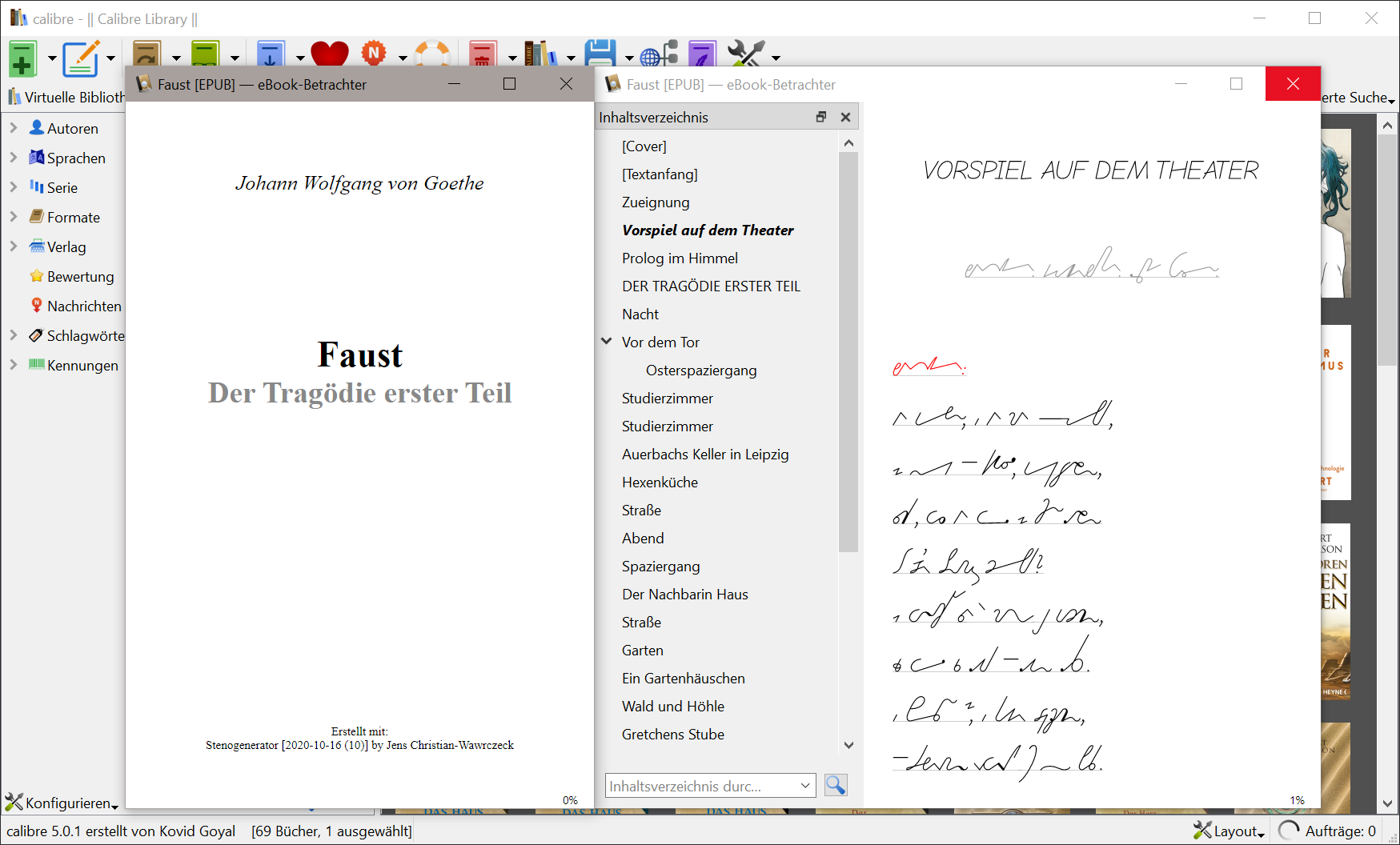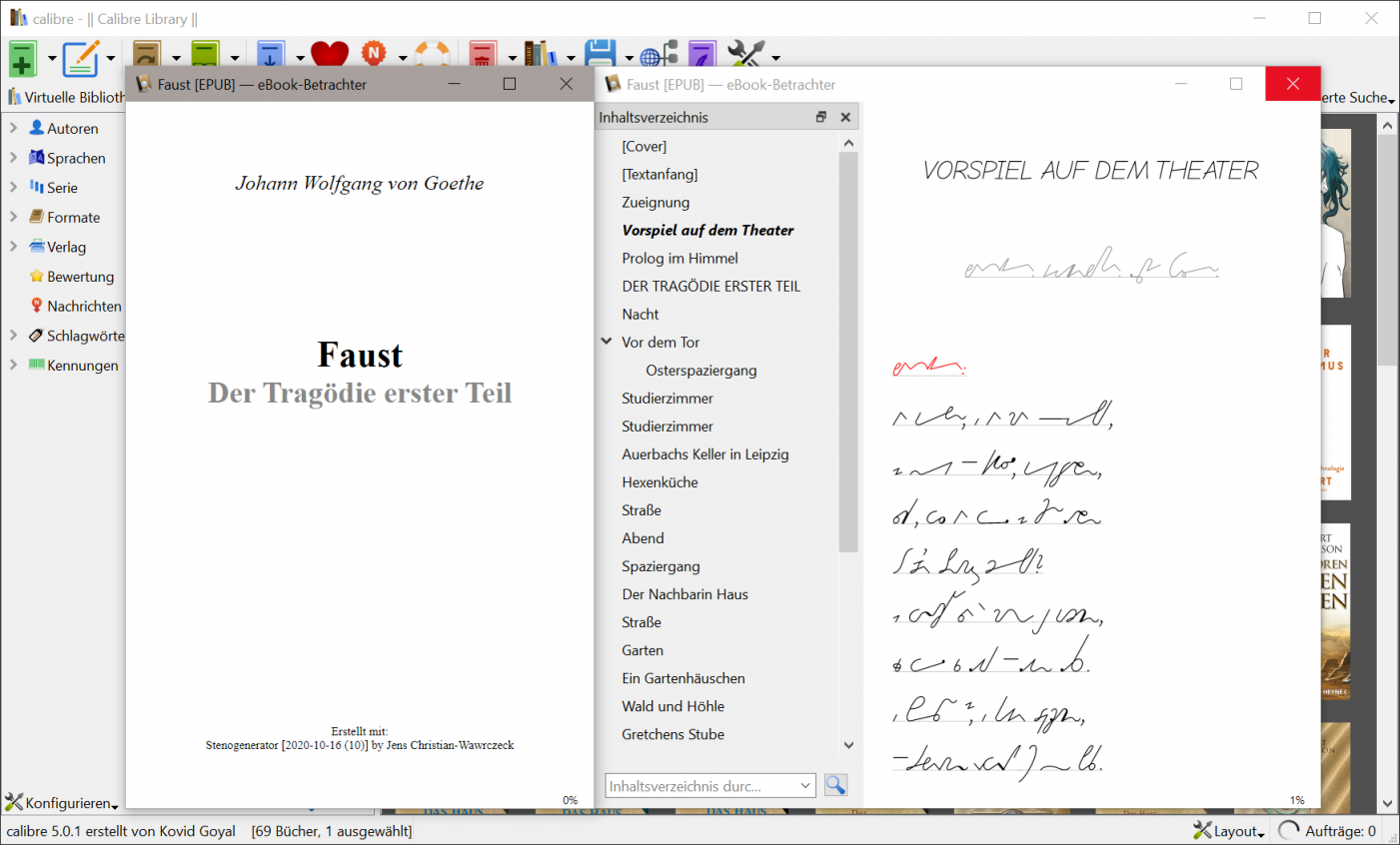
Stenografie in Unicode
Kürzlich habe ich entdeckt, dass bei Unicode unter Proposed New Characters: Pipeline Table die Duployé-Stenografie für eine Aufnahme in Unicode akzeptiert worden ist! Es ist das erste Stenografie-System, das in Unicode augenommen wird. Die Duployé-Stenografie ist ein geometrisches System, ähnlich wie die Pitman-Stenografie, verwendet aber im Unterschied zu dieser normale Zeichen für die Vokale. Eine genaue Beschreibung des Systems gibt es als PDF unter Proposal to include Duployan script and Shorthand Format Controls in UCS.
Die deutschsprachigen Stenografiesysteme (hauptsächlich die deutsche Einheitskurzschrift in Deutschland und Stolze-Schrey in der Schweiz, ferner Gabelsberger) funktionieren nach einem ganz anderen Prinzip. Ich vermute, ihrer Aufnahme in Unicode stünde nichts im Weg – wenn sich nur jemand die Mühe machen würde, ein Gesuch zu schreiben... :)
Es scheint auch einen Computerfont für das Duployé-System zu geben, allerdings ist er nirgens erhältlich. :( Es wäre interessant, zu sehen, wie die Stenografie-Darstellung gelöst worden ist. Stenografiesysteme gehören wohl zu den allerkomplexesten Schriften, wenn es darum geht, Computerfonts zu erstellen.
Stenografiesysteme gehören wohl zu den allerkomplexesten Schriften, wenn es darum geht, Computerfonts zu erstellen.
Allerdings, und zwar wegen der Verbindungen der Buchstaben, jedenfalls bei Schreibschrift-Systemen wie der DEK (mit geometrischen Systemen kenne ich mich nicht aus). Es gibt nicht nur weite und enge Verbindungen, die Zeichen werden auch in verschiedenen Höhen (Stufen) geschrieben (siehe bspw. „Beter“ und „Butter“ in dieser Abbildung). Die vielen Zeichen müßten also auch noch in zig Varianten vorliegen, damit die Verbindungen bei allen Zeichen passen. Und wie soll man die Stufen umsetzen? Die Stufen sind im Grunde unbeschränkt, sodaß Lage-Varianten in der Schrift eigentlich nicht ausreichen.
Ehrlich gesagt befremdet mich ziemlich, was alles in Unicode aufgenommen wird. Für solche Spezialfälle wären in meinen Augen Sondercodierungen sinnvoller.
Die Stufen sind im Grunde unbeschränkt, sodaß Lage-Varianten in der Schrift eigentlich nicht ausreichen.
Das stimmt. Man müsste sich vermutlich aus praktischen Gründen auf vielleicht je fünf Stufen beschränken – jedenfalls in AAT, wo ich mich am besten auskenne, und wohl auch in Graphite. In OpenType wäre vielleicht über Ankerpünkte eine Definition von relativen Stufen möglich, so dass die Stufenzahl unbeschränkt wäre.
In den geometrischen Systemen gibt es eine sehr vergleichbare Komplexität, auch wenn es dort kein Faulmannsches Stufenkonzept gibt wie in den meisten deutschsprachigen Stenografiesystemen. Wie es im Unicode-Vorschlag für das Duployé-System theoretisch gelöst ist, habe ich nicht eingehend studiert.
Ehrlich gesagt befremdet mich ziemlich, was alles in Unicode aufgenommen wird. Für solche Spezialfälle wären in meinen Augen Sondercodierungen sinnvoller.
Warum denn? Die Idee von Unicode ist doch, dass alle Texte, auch die historischen, eindeutig kodiert werden können.
Warum? Die DEK und ihre Vorgänger sind nunmal keine herkömmlichen Buchstabensysteme. Bedeutung haben nicht nur die Zeichen, sondern auch, wie sie stehen und wie sie verbunden werden. Wie soll man das vernünftig codieren? Da stößt das Buchstabenkonzept von Unicode an seine Grenzen.
Natürlich könnte man das durch irgendwelche Kniffe mit OpenType oä. hinkriegen, indem man Funktionen zweckentfremdet, aber das wären bloß schmutzige Tricks. Es geht, aber es geht nicht gut. Es ist ungeheuere Arbeit, fehleranfällig, und schlecht zu warten. So eine Sonderanwendung braucht einfach besondere Werkzeuge, d. h. ein eigenes Dateiformat/eigenes Codierungssystem.
Man kann natürlich ein Taschenmesser um eine Grasklinge erweitern. Besser ist aber, den Rasenmäher zu erfinden.
Was Unicode angeht, so sind auch die Vokale in den Faulmann-Systemen bloss Charaktere. Die Darstellung ist eine Software-Frage. Mit OpenType dürfte es tatsächlich schwierig werden. Graphite ist wohl besser geeignet, oder AAT.
Die Stufen sind im Grunde unbeschränkt, sodaß Lage-Varianten in der Schrift eigentlich nicht ausreichen.
Da soweit ich weiß in der Eilschrift aus mindestens zweistufig hoch- oder tiefgestellten Buchstaben bei großen Zeichen oder Stufenerhöhung in die Grundstufe hinuntergewechselt werden kann (weil das eindeutig ist, also nicht mit einem normalen Stufenwechsel verwechselt werden kann), würden 5 Stufen für eine vollständige Kodierung reichen (wobei 5 Steno-Stufen eigentlich 9 Halbstufen entsprechen).
Mal abgesehen davon, ob man das technisch umsetzten kann, frage ich mich: warum?
Steno ist eine Kurzschrift um handschriftlich schnell Informationen zu notieren. Es macht doch irgendwie wenig Sinn – außer für Steno-Lehrbücher – das am Computer nachmachen zu wollen, zumal man die Zeichen ja im Leben nie so schnell eingeben, wie schreiben könnte. Und wenn man sie schnell eingeben könnte, wäre es ja sinnvoller, dass die Software das gleich in normale Schrift umsetzt, dann spart man sich den Schritt des anschließenden „Übersetzens“ …
Und genau darum geht es. Durch die computergestützte Generierung ausreichender Menge stenografischen Textes die Lesefähigkeit zu verbessern. Nur durch viel Lesen kommt man vom Buchstabieren weg, hin zum Erkennen ganzer Wortbilder und damit zum "flüssigen" Lesen. Was sich am Ende positiv auf die eigene stenografische Schreibleistung auswirkt, einem ganz praktischen Nutzen. Von der Ästhetik der Schrift mal ganz abgesehen. 🙂